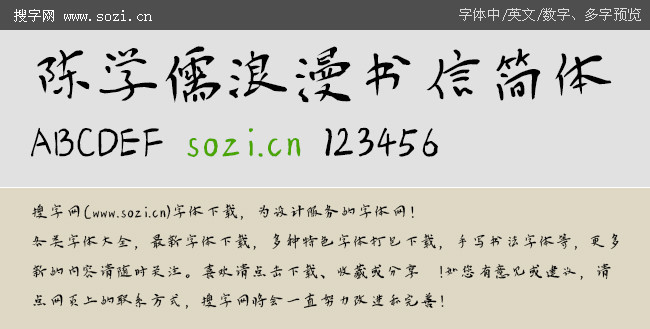
陳學(xué)儒浪漫書信簡體
搜字網(wǎng)給大家提供一款陳學(xué)儒浪漫書信簡體中文字體下載,陳學(xué)儒浪漫書信簡體是一款手寫風(fēng)格的書法字體。字體字形飄逸,筆鋒細(xì)膩,充滿浪漫氣息,適合應(yīng)用于海報(bào)設(shè)計(jì)、書籍裝幀、畫冊(cè)封面、產(chǎn)品包裝設(shè)計(jì)等應(yīng)用。(本字體為個(gè)人非商用版,如需要商用請(qǐng)聯(lián)系作者購買版權(quán))